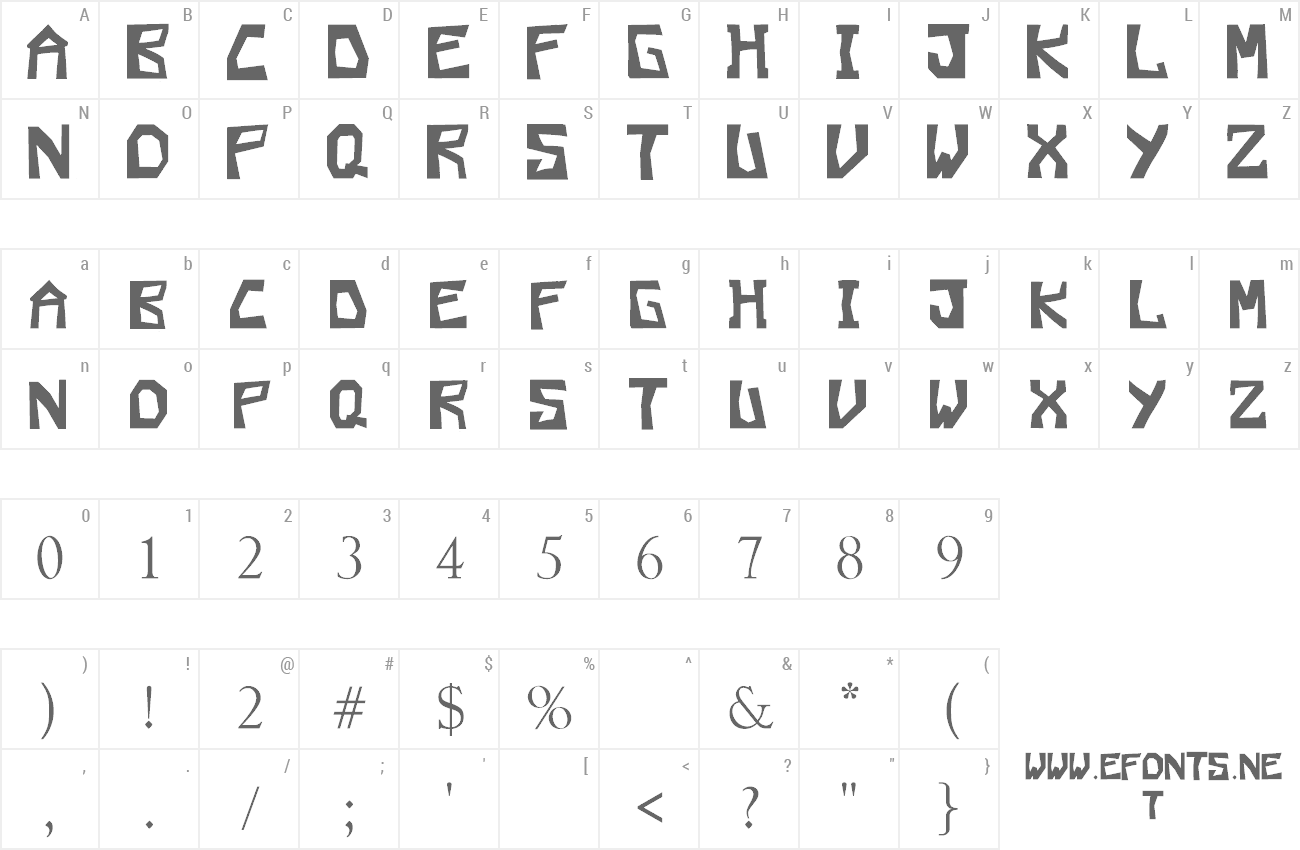
| Font name: | Valparaletra |
| Author: | David Koffe |
| Note by David Koffe | |
| Esta letra tiene una significancia especial, fue creada bajo un trabajo fotográfico, en el cual se realizo una escurcion en la ciudad de valparaiso, en donde se tomo un registro fotográfico y en base a este registro se genero VALPARALETRA. |